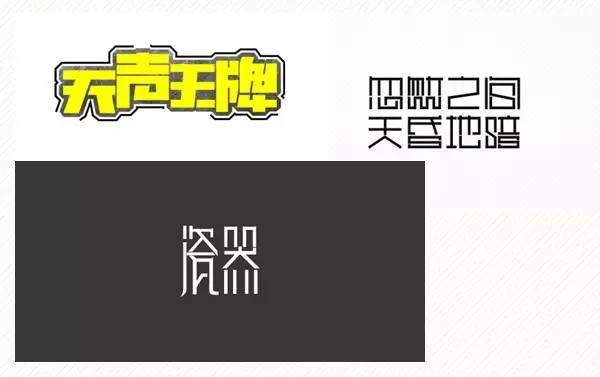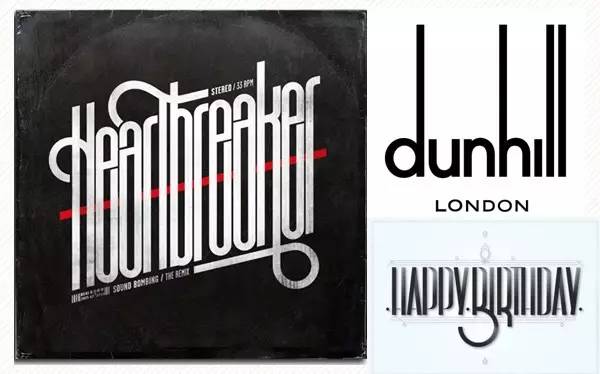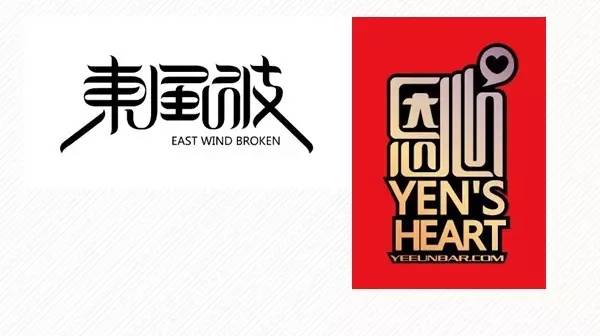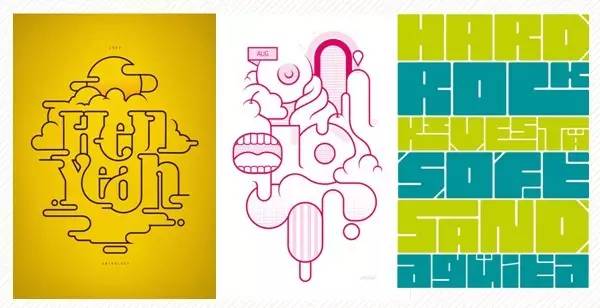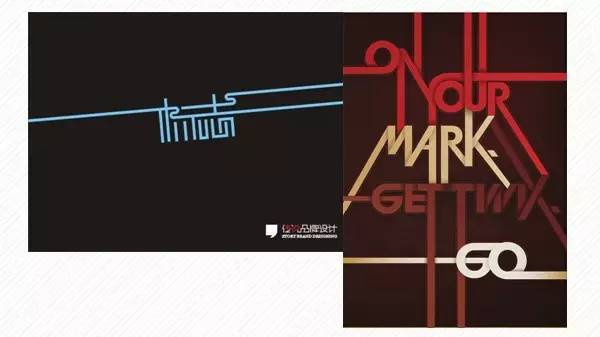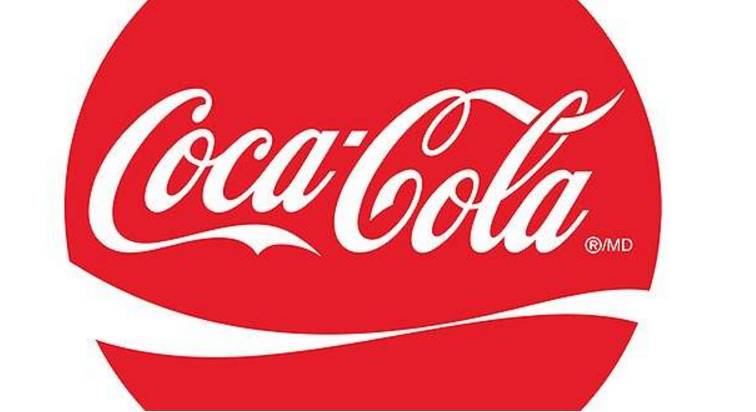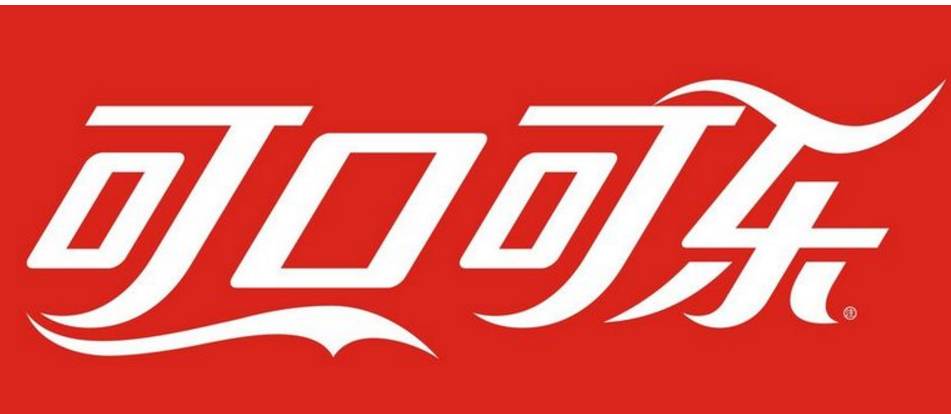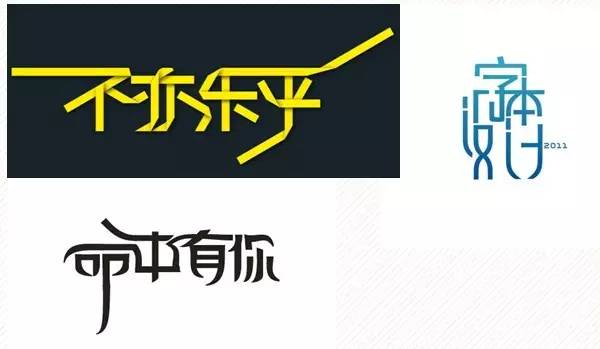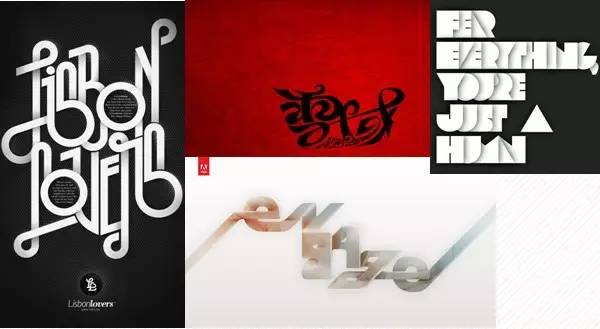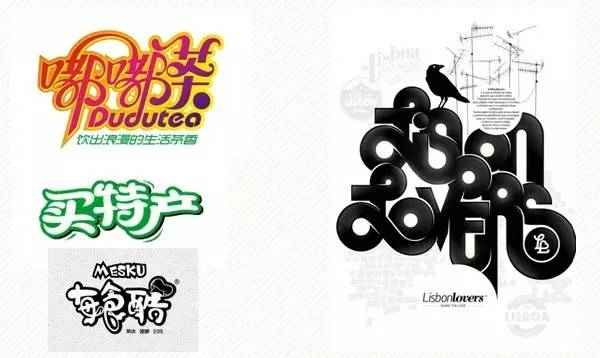
设计中文字体的创意方法,汇总了 17 种设计字体的方法
引言:做设计三大难:没素材,没灵感和甲方又不肯买字体!特别是中文字体,更加麻烦。今天给大家分享17招中文字体设计方法,拿走不谢!
1、替换
替换法是在统一形态的文字元素加入另类不同的图形元素或文字元素。其本质是根据文字的内容意思,将文字的局部替换。将文字的内涵外露,在形象和感官上都增加了一定的艺术感染力。
2、共用
“笔画公用”是文字图形化创意设计中广泛运用的形式。文字是一种视觉图形,它的线条有着强烈的构成性,可以从单纯的构成角度来看到笔画之间的异同,寻找笔画之间的内在联系,找到他们可以共同利用的条件,把它提取出来合并为一。
3、叠加
叠加法是将文字的笔画互相重叠或将字与字、字与图形相互重叠的表现手法。叠加能使图形产生三度空间感,通过叠加处理的实行和虚形,增加了设计的内涵和意念,以图形的巧妙组合与表现,使单调的形象丰富起来。
4、分解重构
分解重构发是将熟悉的文字或图形打散后,通过不同的角度审视并重新组合处理,主要目的是破坏其基本规律并寻求新的设计生命。
5、俏皮设计
把横中间拉成圆弧,角也用圆处理,这个方法还有重要一点就是色彩,字体处理上加上色彩的搭配才能作出好的俏皮可爱字体。
6、尖角
把字的角变成直尖、弯尖、斜卷尖;可以是竖的角可以是横的角,这样文字看起来会比较硬朗。
7、断肢
把一些封合包围的字,适当的断开一口出来 ,或把左边断一截,或右边去一截。注意:要在能识别的情况下适当断肢。
8、减细法
所有字体横和竖变细。
9、错落摆放
把左右改为左上左下,上下排,或斜排就是一边高一边低,让文字错落有致排列。
10、方块
把所有字的弯全改成横平竖直,四四方方的。
11、卷叶
把所有字的最左或最右横或竖或点全卷起来,像浪花一样,此法,一般是找到一个点或线后转曲,用最下面或最左边或最右边的两个点向一边拉,以加节点的方法拉成一个圈,然后把他转成倒圆角后,留着最后面的两点,慢慢删除中间的节点。
12、横细竖粗法
选定个字体后,把横比划减细竖比划加粗。类似传统宋体字,横细竖粗撇如刀。
13、上下拉长
把字变细,然后上下拉长,类似条形码的感觉。
14、结构转变
可以说是代替法的一种,把竖或横线或折换成其他比划。
15、照葫芦画瓢
先画一个几何图形,方形或矩形或星形,然后把字放进去,照几何图形路线制作字体。
16、局部笔画拉长
算是拉长法的一种,找到标志中的一个点或线作为重点把他拉长,使得处理好的字体,再加一笔更是画龙点睛之作。
17、洋为中用
实在想不到,就参考一下英文字体的设计风格,同样可以找到很多好灵感。可口可乐不就是个好例子吗?